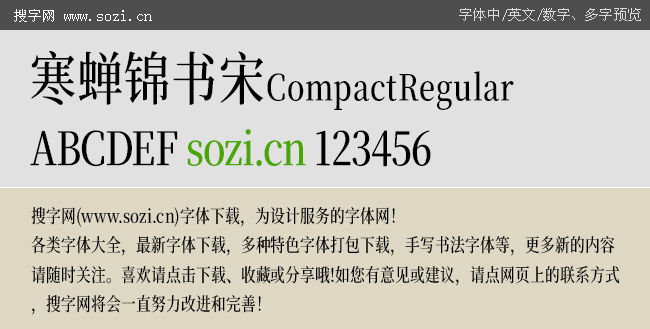
寒蟬錦書(shū)宋CompactRegular
搜字網(wǎng)給大家提供一款寒蟬錦書(shū)宋CompactRegular中文字體下載,寒蟬錦書(shū)宋是基于思源宋體進(jìn)行修改的一款字體,在思源宋的基礎(chǔ)上添加圓角,變成更加溫潤(rùn)的宋體,排版細(xì)節(jié)優(yōu)化,重構(gòu)字重比例,使字體粗細(xì)更加均衡,便于閱讀,包含12種字重文件,適用于標(biāo)題設(shè)計(jì)、海報(bào)設(shè)計(jì)、書(shū)籍排版以及網(wǎng)頁(yè)設(shè)計(jì)等應(yīng)用。